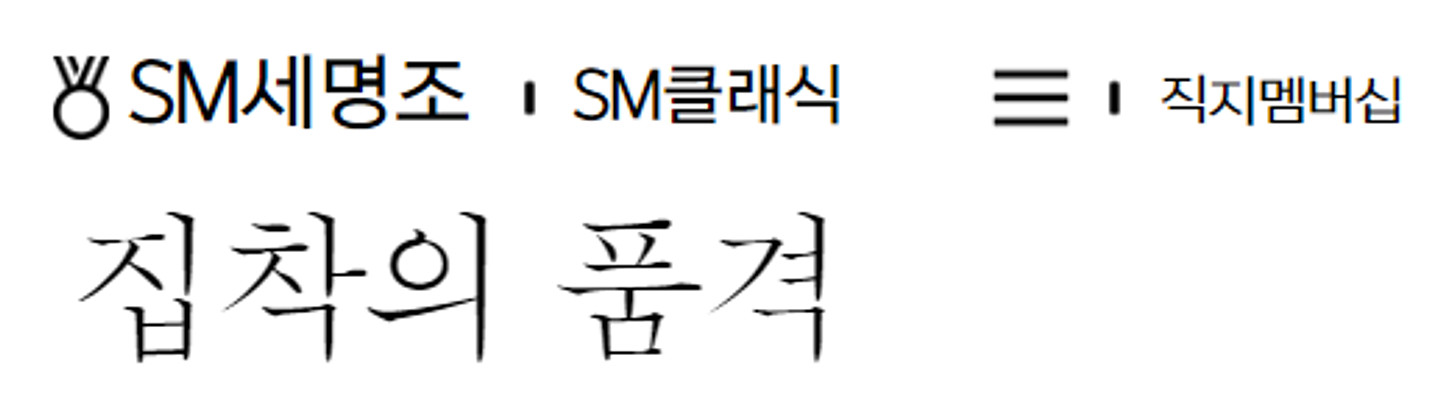
안녕하세요. 언제나 답변해주시는 분들 감사드립니다! 디자인적 수정작업이 들어가있는데, 혹시 원 서체 폰트를 아시는 분 있을까요? -얇은 명조체 -ㅈ이 ㅡ와 ㅅ 합친 모양 -ㅇ위의 삐침이 있음 이게 특징입니다. 비슷한 특징을 가진 명조체라면 위폰트가 아니어도 알려주시면 감사하겠습니다! 좋은 하루되세요.
SM세명조
SM세명조에 변형을 준 것 같습니다.